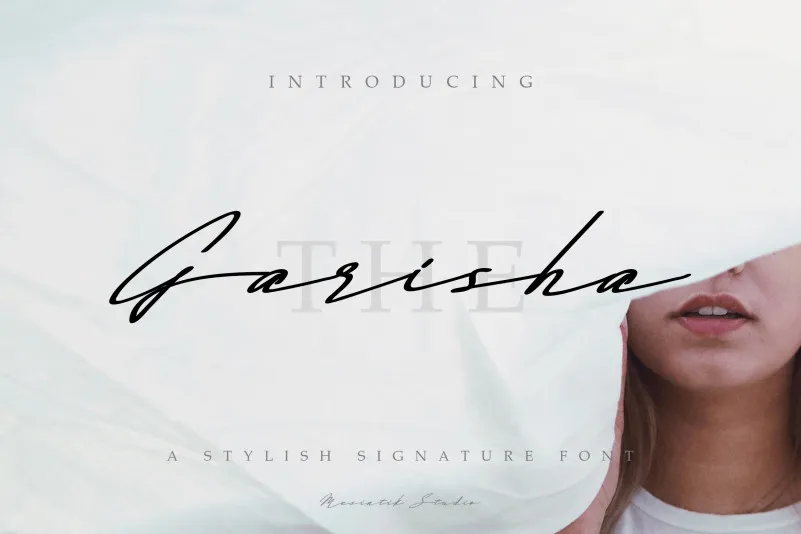
The Garisha Signature Font – Download Grátis
A Garisha é uma fonte de escrita de chamada que destaca-se pela elegância e suavidade dos seus traços. Ideal para vários projetos visuais, a Garisha oferece um estilo sofisticado e versátil que vai desde cartões de convite até o trabalho de design gráfico. Seu nome já sugere uma forte personalidade, mas é essa fonte que realmente transforma qualquer projeto em algo único e memorável. Mesinitik Studio criou a Garisha com um propósito claro: inspirar seus usuários a fazerem belos trabalhos manuais. Esta não é apenas uma fonte; ela é o retrato de sua filosofia, oferecendo ao designer a liberdade de explorar e expressar suas ideias de maneira tão criativa quanto desejar.
Designer: Mesinitik Studio